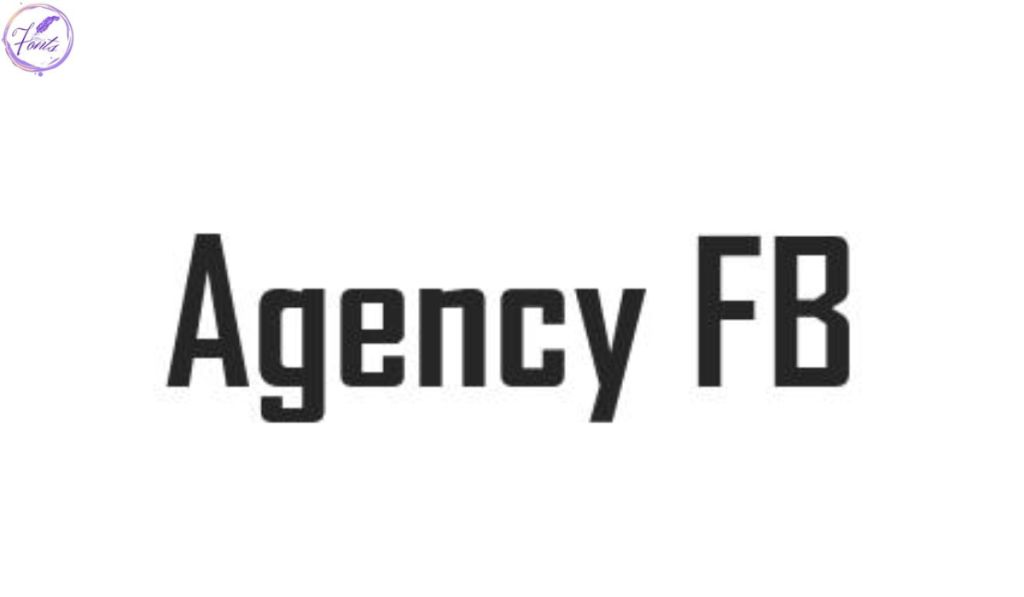
Agency FB font việt hóa
Tác giả: David Berlow, Morris Fuller Benton
Ngày phát hành: 1990
Ngôn ngữ: Tiếng Việt, nhiều ngôn ngữ khác
Bộ Font: Agency FB
Phân loại: Cá tính, độc đáo
Kiểu chữ: Sans-serif (không chân)
Độ dày: Thin, Light, Regular, Bold, Black, Compressed, Condensed, Extended, Wide
Agency FB Font là một kiểu chữ mạnh mẽ và hiện đại, được thiết kế bởi David Berlow và Morris Fuller Benton vào năm 1932. Với những đường nét gọn gàng và sắc sảo, font này mang lại cảm giác chuyên nghiệp và thanh lịch cho bất kỳ dự án thiết kế nào. Agency fb font thường được sử dụng trong các thiết kế logo, tiêu đề, và các tài liệu quảng cáo nhờ vào tính dễ đọc và sự nổi bật của nó. Đặc biệt, font này đã được Việt hóa hoàn chỉnh, giúp người dùng dễ dàng sử dụng trong các văn bản tiếng Việt mà không gặp bất kỳ khó khăn nào.
Đánh giá agency fb font
Agency FB Font nhận được nhiều đánh giá tích cực từ cộng đồng thiết kế đồ họa. Điểm mạnh của font này là sự kết hợp hoàn hảo giữa tính thẩm mỹ cao và tính ứng dụng rộng rãi, phù hợp cho nhiều loại dự án khác nhau. Nét chữ sắc sảo và dễ đọc của agency fb font không chỉ tạo nên sự cuốn hút mà còn mang lại cảm giác chuyên nghiệp và hiện đại cho các thiết kế. Khả năng Việt hóa xuất sắc cũng là một điểm cộng lớn, giúp font này dễ dàng tích hợp vào các thiết kế tiếng Việt, làm cho các dự án trở nên nổi bật và thu hút hơn.